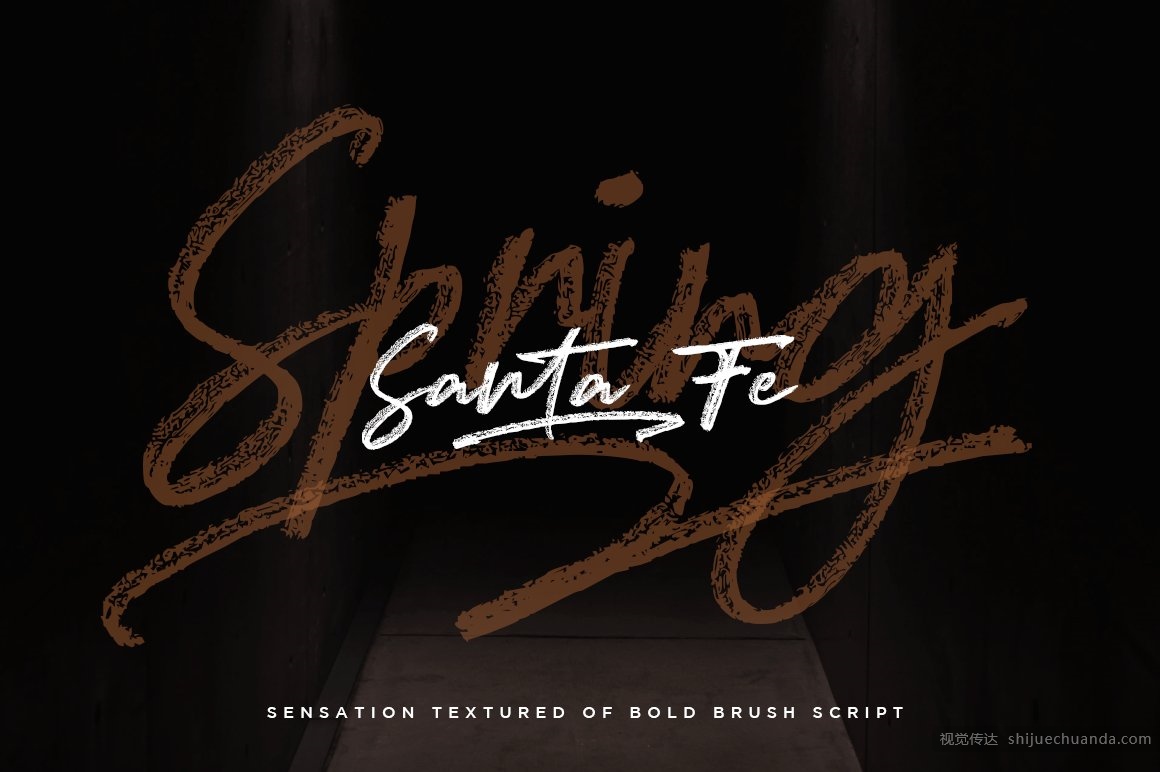
喷沙纹理质感笔刷字体 Sandblast Extreme Texture Brush Font
Sandblast是一种极富质感的笔刷字体,用手写的笔迹对其进行了设计,可以在Photoshop中将此图层与蒙版一起使用,看起来真的很自然。Sandblast Script包含了几对连字,使所有内容看起来完全是手工完成的。